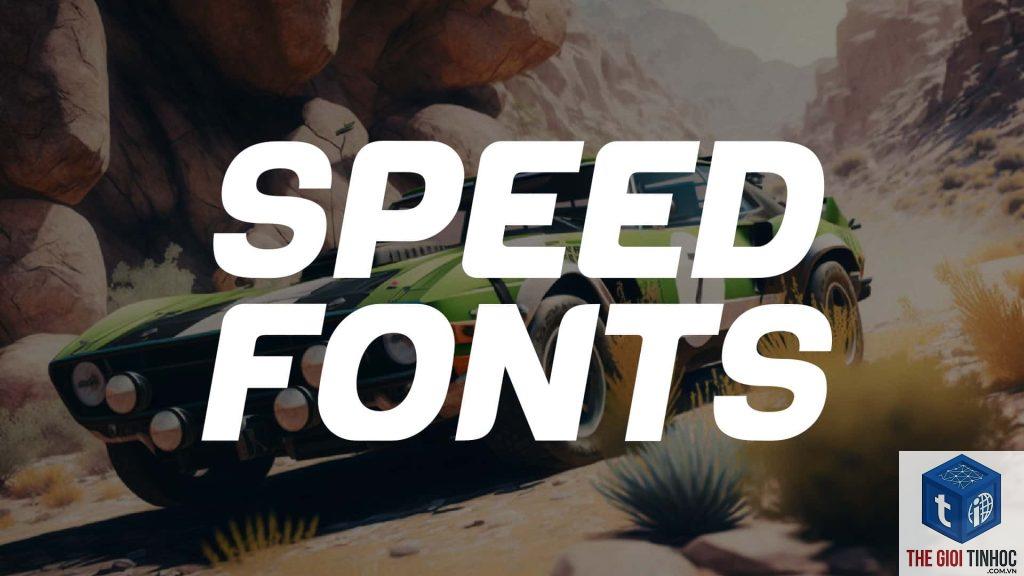
Khi xây dựng một website WordPress, tốc độ tải trang luôn là yếu tố sống còn. Nhiều người tập trung vào hosting, hình ảnh hay plugin mà quên mất một chi tiết tưởng chừng nhỏ nhưng lại có tác động lớn: font chữ. Font WordPress ảnh hưởng tốc độ một cách trực tiếp và rõ rệt, từ việc tăng dung lượng tải xuống đến chặn hiển thị nội dung. Bài viết này sẽ phân tích chi tiết cơ chế, mức độ ảnh hưởng và cách tối ưu font chữ để website của bạn luôn nhanh như chớp.
Font WordPress Ảnh Hưởng Tốc Độ Như Thế Nào?
Font chữ không chỉ đơn thuần là kiểu chữ bạn nhìn thấy trên màn hình. Mỗi font chữ là một tập hợp các tệp tin chứa thông tin về hình dạng, kích thước và kiểu dáng của từng ký tự. Khi bạn sử dụng font từ bên ngoài (Google Fonts, Adobe Fonts), trình duyệt phải tải toàn bộ tệp font đó trước khi hiển thị văn bản. Quá trình này làm tăng thời gian tải trang và gây ra hiện tượng Flash of Invisible Text (FOIT) – nội dung biến mất trong giây lát.
Có ba cơ chế chính khiến font WordPress ảnh hưởng tốc độ:
- Dung lượng tệp font lớn: Một font chữ có thể nặng từ 20KB đến 200KB, thậm chí hơn nếu là font đa dạng (bold, italic, light). Nhân với số lượng font bạn dùng, dung lượng tăng lên đáng kể.
- Yêu cầu HTTP bổ sung: Mỗi font chữ từ bên ngoài tạo ra một hoặc nhiều request HTTP riêng. Càng nhiều request, trình duyệt càng mất thời gian xử lý.
- Chặn hiển thị nội dung: Trình duyệt thường ẩn văn bản cho đến khi font được tải xong. Điều này làm tăng thời gian Largest Contentful Paint (LCP) – một chỉ số quan trọng trong Core Web Vitals.
- Cải thiện tốc độ tải trang: Giảm thời gian LCP và FCP, giúp website nhanh hơn rõ rệt.
- Tăng trải nghiệm người dùng: Người dùng không phải chờ đợi nội dung hiển thị, giảm tỷ lệ thoát trang.
- Cải thiện SEO: Core Web Vitals tốt hơn giúp website lên top Google.
- Tiết kiệm băng thông: Giảm dung lượng tải xuống, đặc biệt quan trọng với người dùng di động.
Tác Động Của Font Chữ Đến Core Web Vitals
Google đã đưa Core Web Vitals vào yếu tố xếp hạng. Font WordPress ảnh hưởng tốc độ trực tiếp đến ba chỉ số này:
| Chỉ số | Mô tả | Mức độ ảnh hưởng |
|---|---|---|
| LCP (Largest Contentful Paint) | Thời gian hiển thị phần tử nội dung lớn nhất | Cao – font chữ thường là một phần của văn bản chính |
| FCP (First Contentful Paint) | Thời điểm hiển thị nội dung đầu tiên | Trung bình – font chậm làm trì hoãn hiển thị chữ |
| CLS (Cumulative Layout Shift) | Độ dịch chuyển bố cục | Thấp – nếu không dùng font fallback phù hợp |
Khi font chữ tải chậm, LCP có thể tăng từ 1 giây lên 3-4 giây. Điều này không chỉ làm giảm trải nghiệm người dùng mà còn khiến website mất thứ hạng trên Google.
Phân Loại Font Chữ Và Mức Độ Ảnh Hưởng
Font Hệ Thống (System Fonts)
Font hệ thống là những font có sẵn trên thiết bị của người dùng như Arial, Times New Roman, Georgia. Khi sử dụng font này, trình duyệt không cần tải thêm bất kỳ tệp nào. Font WordPress ảnh hưởng tốc độ ở mức thấp nhất với loại font này. Tốc độ tải trang gần như không bị ảnh hưởng.
Font Google (Google Fonts)
Đây là loại font phổ biến nhất trên WordPress. Google Fonts miễn phí, đa dạng và dễ tích hợp. Tuy nhiên, mỗi font Google đều phải tải từ máy chủ của Google. Nếu bạn dùng nhiều biến thể (regular, bold, italic), dung lượng tải có thể lên đến 300KB. Font WordPress ảnh hưởng tốc độ ở mức trung bình đến cao với loại font này.
Font Tùy Chỉnh (Custom Fonts)
Font tùy chỉnh thường được lưu trên hosting của bạn hoặc dịch vụ bên thứ ba. Chúng có thể nặng hơn font Google do không được tối ưu cho web. Font WordPress ảnh hưởng tốc độ ở mức cao nhất nếu bạn không nén hoặc chọn định dạng phù hợp.
So Sánh Tốc Độ Giữa Các Loại Font
| Loại font | Dung lượng trung bình | Số request | Thời gian tải (ước tính) |
|---|---|---|---|
| Font hệ thống | 0 KB | 0 | 0 ms |
| Google Fonts (1 biến thể) | 20-50 KB | 1-2 | 100-300 ms |
| Google Fonts (nhiều biến thể) | 100-300 KB | 3-5 | 500-1000 ms |
| Font tùy chỉnh (WOFF2) | 30-100 KB | 1 | 200-500 ms |
| Font tùy chỉnh (TTF/OTF) | 100-500 KB | 1 | 500-2000 ms |
Rõ ràng, font hệ thống là lựa chọn tối ưu nhất về tốc độ. Tuy nhiên, nếu bạn muốn giữ tính thẩm mỹ, cần cân nhắc kỹ giữa số lượng font và biến thể sử dụng.
Lợi Ích Của Việc Tối Ưu Font Chữ
Hạn Chế Khi Sử Dụng Font Hệ Thống
Dù font hệ thống nhanh nhất, nhưng chúng có hạn chế về mặt thẩm mỹ. Font hệ thống thường đơn giản, thiếu cá tính và không tạo được sự khác biệt cho thương hiệu. Nếu bạn chạy website thương mại điện tử hoặc blog cá nhân, font tùy chỉnh vẫn là lựa chọn tốt hơn. Font WordPress ảnh hưởng tốc độ là điều không thể tránh, nhưng
Mức độ ảnh hưởng phụ thuộc vào số lượng font, biến thể và cách tải. Trong nhiều trường hợp, font chữ có thể làm tăng thời gian tải trang từ 0.5 đến 2 giây. Với website dùng nhiều font, con số này có thể lên đến 3-4 giây.
Có nên dùng Google Fonts cho WordPress không?